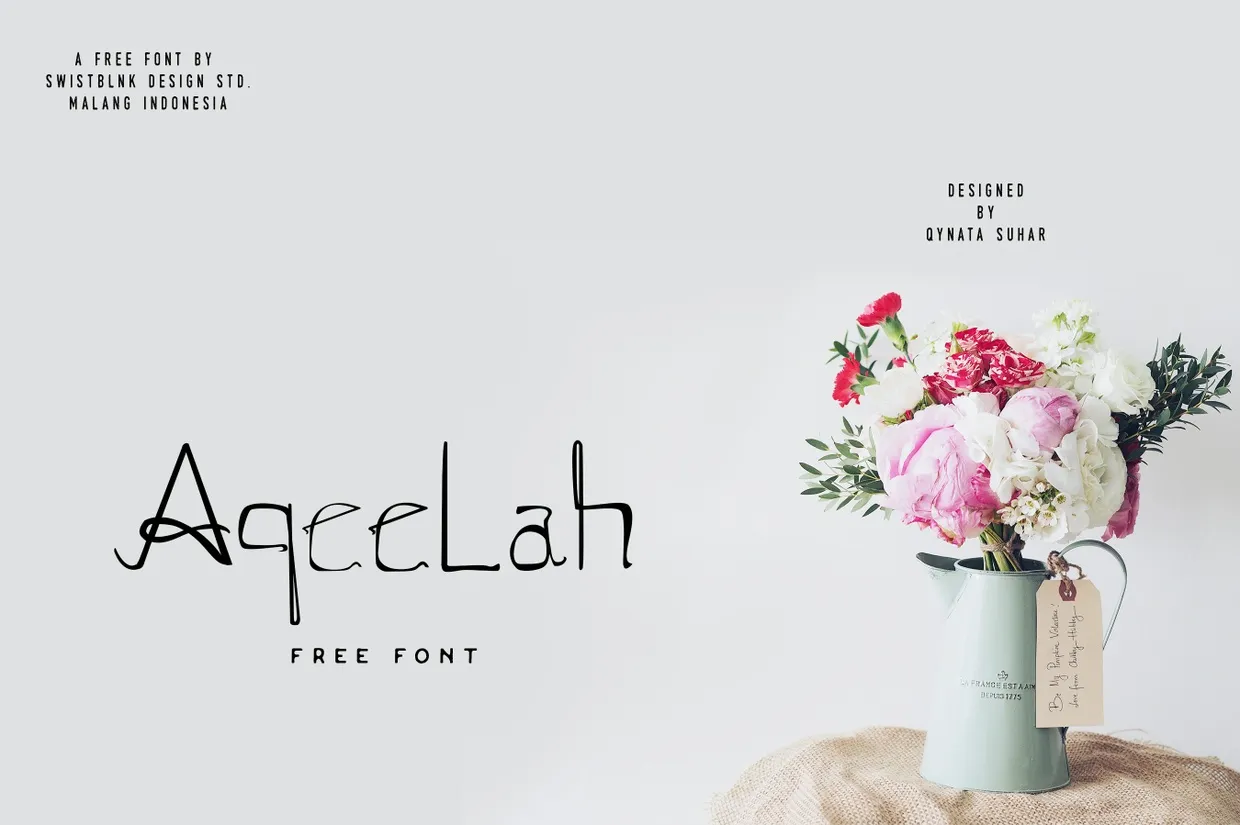
Aqeelah Font – Download Grátis
Aqeelah Font é uma elegante fonte feita à mão criada por Hamilton, disponível gratuitamente para uso pessoal e comercial. Esta fonte expressa profundidade e sofisticação, perfeita para trabalhos de escrita livre ou design editorial. Como qualquer fonte feita à mão, ela oferece um toque único que pode destacar seus projetos de marketing digital ou criações gráficas. Aqeelah é não apenas uma ferramenta versátil, mas também um investimento em qualidade e estética única para seu projeto. Seja você um designer profissional ou iniciante, essa fonte livre vai adicionar uma camada especial a seus trabalhos. Recomendamos fazer uma doação por meio de plataformas como PayPal ou outras opções financeiras se desejar apoiar o desenvolvimento contínuo desta fonte maravilhosa.